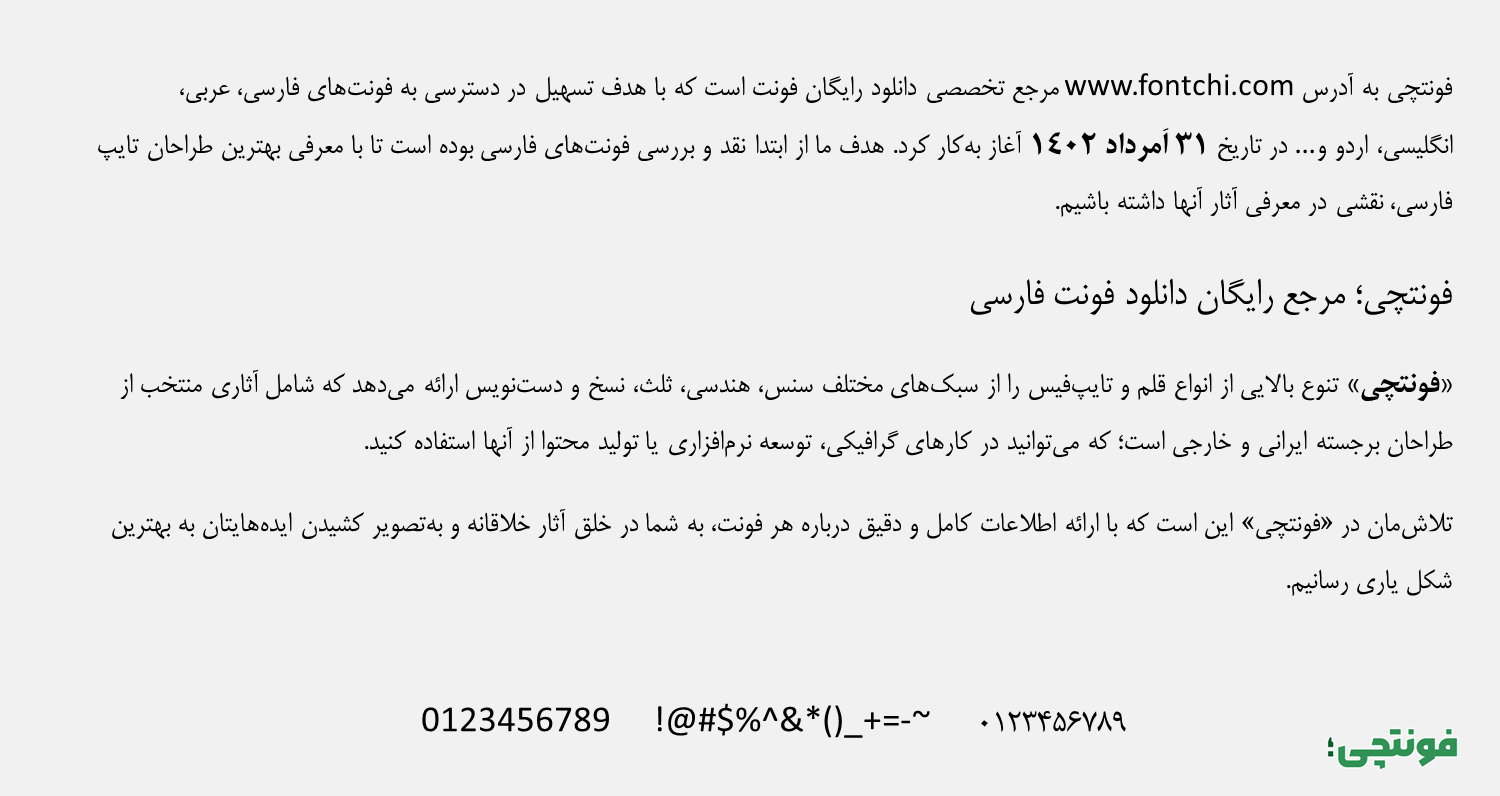
فونت بی میترا (B Mitra)
فونت بی میترا یا فونت میترا (به انگلیسی: B Mitra) یکی دیگر از سری فونتهای بی است که به سبک خط نسخ طراحی شده و دارای ظاهری رسمی است. در این مطلب با دانلود رایگان فونت بی میترا با شما همراه هستیم که میتوانید از این فونت برای نامههای اداری، فونت رسمی و مطبوعات از آن استفاده کنید.
فونت B Mitra توسط شرکت برنا رایانه در سال ۱۳۷۹ آخرین آپدیت خود را داشته است که ورژن ۲.۰۱ میباشد. درست زمانی که کامپیوترها در حال ورود به خانههای مردم بودند؛ هرچند با سرعت بسیار پایین که یکباره در دهههای ۸۰ و ۹۰ روند رو به رشد زیادی گرفتند.
پیشنمایش و امکانات فونت بی میترا (B Mitra)
فونت بی میترا دارای ظاهری کاملا رسمی است که مشابه با فونت بی نازنین بیشتر برای استفاده در نامههای رسمی و اداری، صنعت چاپ و کتاب، فونت تحقیفات و پروژههای تحصیلی یا فونت نوشته آگهی چاپی در تبلیغات محیطی ممکن است مورد استفاده قرار گیرد.
حروف در این فونت فارسی دارای ظاهری خوانا هستند که از خط نسخ به ارث بردهاند. از نقاط ناپیوسته با ظاهری لوزی شکل استفاده شده است که در متون با اندازه بزرگتر، ظاهر فونت نمایشتر میشود. این فونت نیز دارای ساختاری است که سایز ۱۴ در آن بیشتر مورد استفاده قرار میگیرد و خوانایی لازم را دارد.
خوانایی این فونت در این سایز روی حالت معمولی است که هر فرد از سنین پایین گرفته تا بزرگسال میتواند بهسادگی آن را مطالعه کند. اما برای افرادی که مشکلات بینایی یا ضعف چشم داشته باشند شاید بهتر باشد از اندازه بزرگتری استفاده کنید.
در تصویر فوق حالت پیشنمایش فونت بی میترا را مشاهده میکنید که شکل حروف در نسخه معمولی و بولد دارای ساختاری یکپارچه است و در این متنی سعی شده تا ترکیبی از حروف و اعداد فارسی، در کنار متن انگلیسی این فونت نمایش داده شود.
دندانهها، چشمی حروف، گردیها و زوایا در این فونت دارای ظاهری لاغر هستند که با زاویه نسبتا خاصی چیدمان آنها در برخی حروف مثل «ل، ش، ن، س، ص، ض» به آن شکل داده شده تا فونت کمی به سبک ثلث نیز نزدیک باشد. در این فونت اعداد استاندارد فارسی نیز قرار دارد.
لازم به ذکر است که فونت B Mitra از زبان فارسی یا سایر زبانهای خاورمیانهای پشتیبانی نمیکند و صرفا یک فونت فارسی است. اما برای زبانهای خاورمیانهای، تمامی ترکیبات و حروفی که یکسان با رسمخط فارسی هستند قابل استفاده بوده و برای زبان عربی نیز برخی ترکیبات که شامل حروف با همزه هستند را شامل میشود.